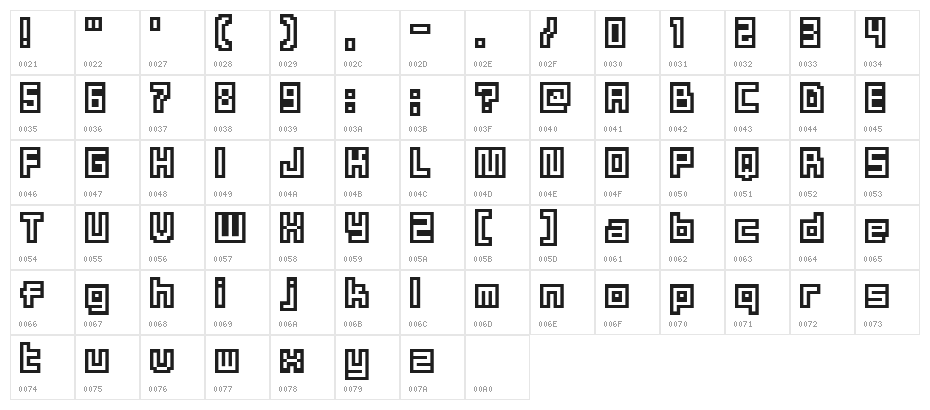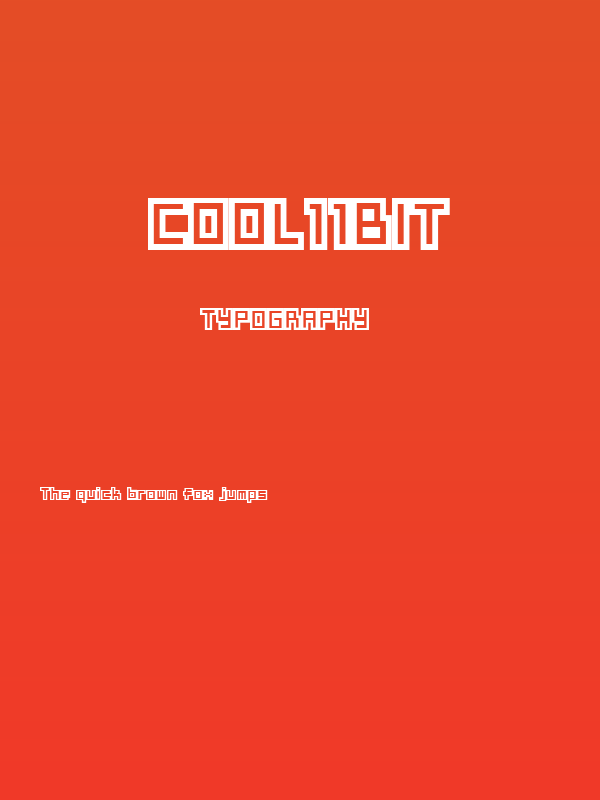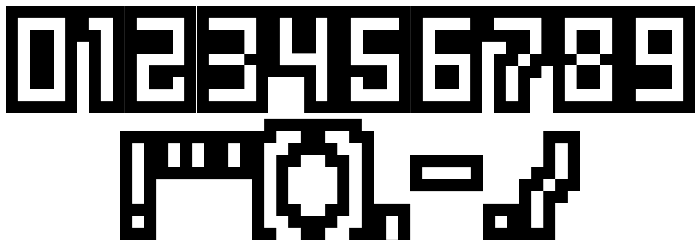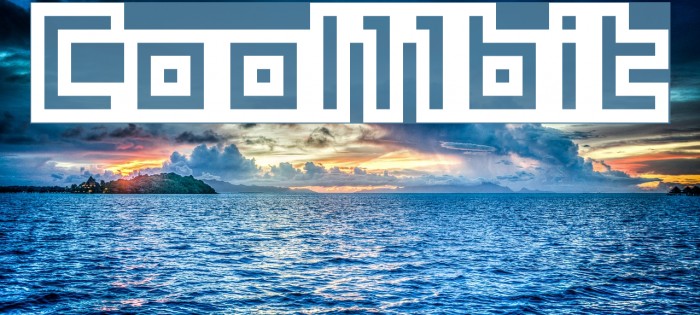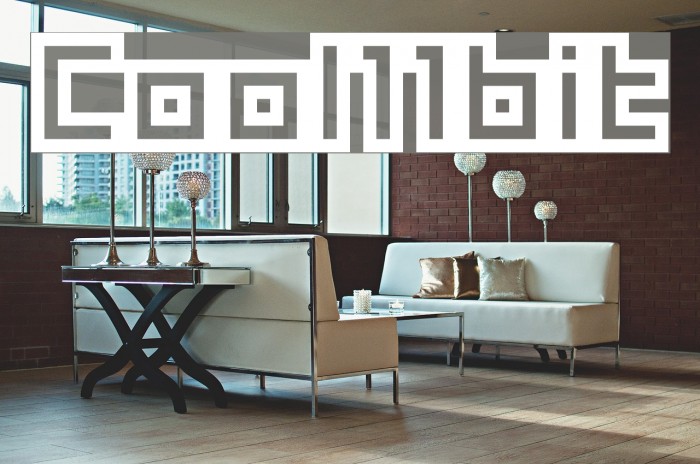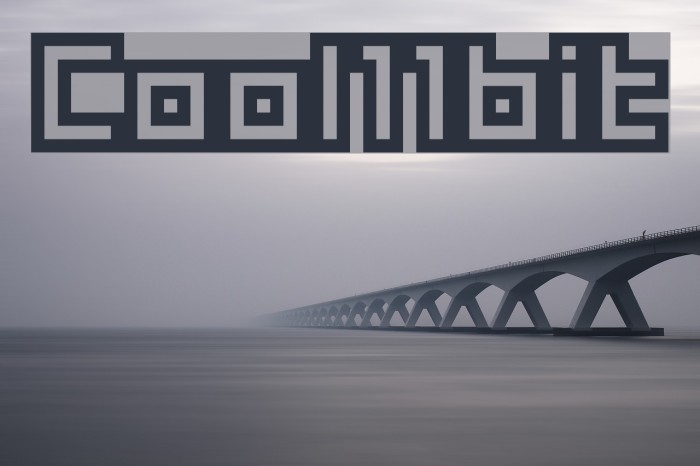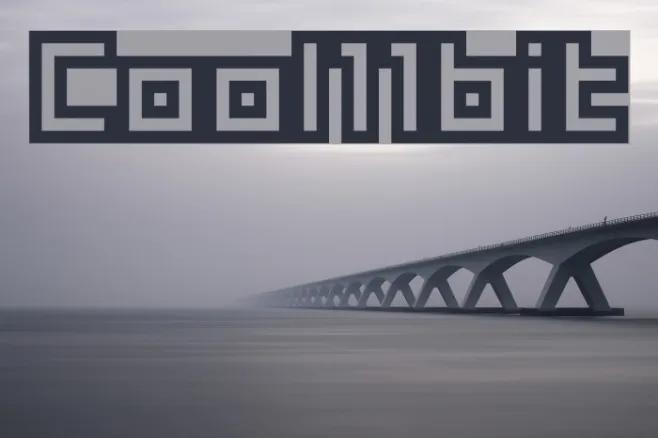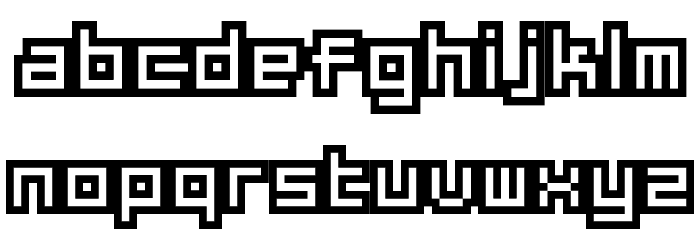
Cool11bit Font
| Gesamtstil | Retro, Digital |
| Vorgeschlagene Projekte | Ideal for video game graphics, retro-themed posters, digital art, and tech-related branding. |